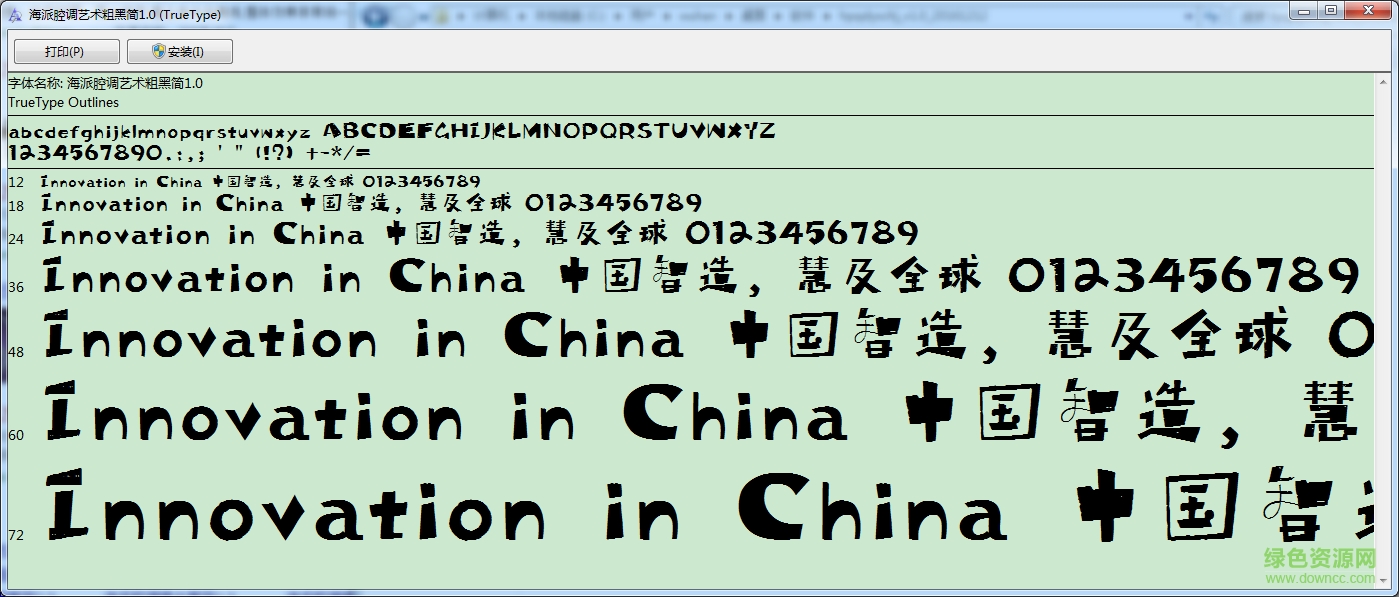
shanghaiface art boldgb1.0字體又叫海派腔調(diào)藝術(shù)粗黑,這款字體粗細(xì)相間,濃墨重彩,非常有特色,適合用在海報設(shè)計或是地方文化宣傳手冊上,喜歡這款字體的朋友快來下載吧!
宋體就是以一套宋體的筆形構(gòu)成,黑體就是以—套黑體的筆形構(gòu)成,但相對于創(chuàng)意性個體,就可以根據(jù)不同創(chuàng)意源點進(jìn)行變換,通過種種變換手法的處理,往往能帶來別具一格的新型字形。